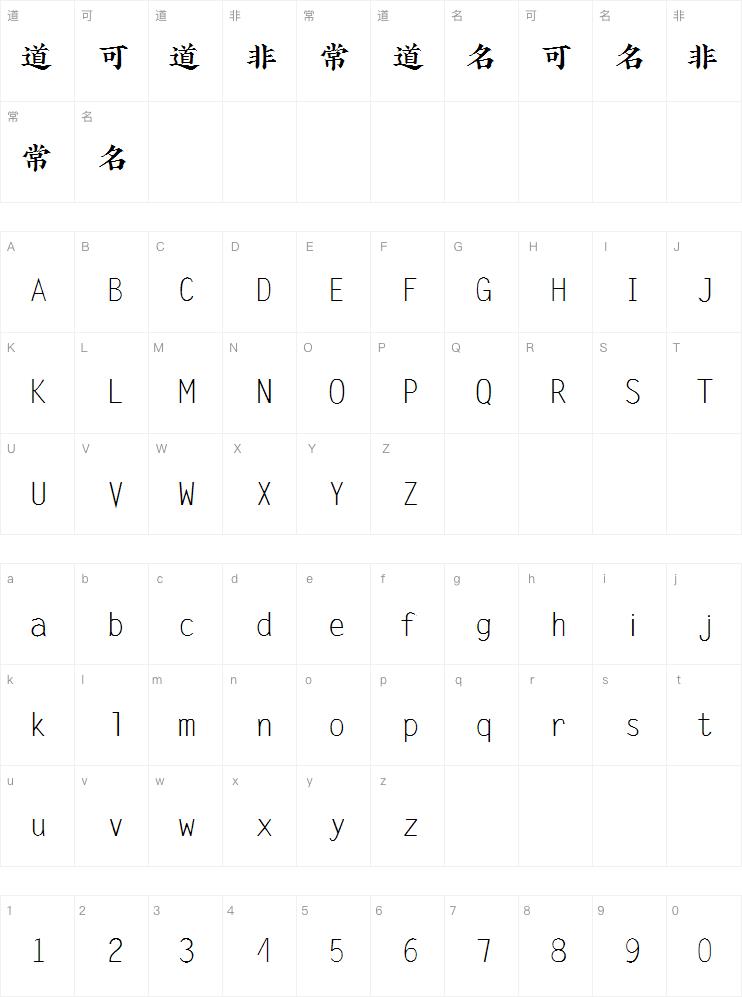
汉呈正文宋体
汉呈正文宋
汉呈正文宋体是一款融合汉代书法风骨与现代宋体规范的创新型字体。其字形以宋体骨架为基础,融入汉代简牍的朴拙气息,横画纤细如丝,竖笔浑厚似柱,转折处方圆相济,保留宋体“横平竖直”的端严特质,同时通过微妙的楔形笔画与波势处理,传递出汉代隶书的古雅意韵。整体结构疏密得当,重心沉稳,既具备宋体字的清晰可辨性,又因笔画起收处的顿挫变化与局部墨色枯润对比,增添了金石镌刻的厚重感。适用于古籍整理、文化专题设计、传统品牌视觉系统等场景,既能承载大篇幅正文的阅读需求,亦可通过字形细节展现历史文脉的深邃美感,呈现“汉风今韵”的跨界融合魅力。